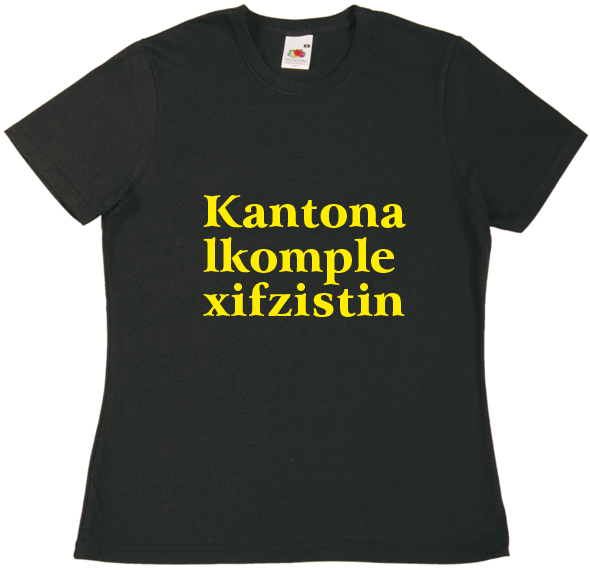
Umlaute in TTFs erstellen: simples Tool?
Komplexifizist!
Geil. Damit will ich ein T-Hemd.
Ist „Kantoniker“ eine Schweizer Spezialität? Irgendwie kommt mir der Begrif so gänzlich unbekannt vor…
:? Google kennt den auch nicht.
Bitte, wie können denn ausgerechnet Schriftgelehrte so unkreativ sein? :o
Während das Kirchenrecht den Kanoniker schon lange kennt, hat der Autor für den Fall der vorliegenden Polemik den "Kantoniker" eigens erfunden.
Dieser Begriff ist positiv diskriminierend. Er soll zeigen, dass Schweizer im Allgemeinen und die bezaubernde NinaS im Besonderen liebenswerte Sonderlinge sind, die ihr kleines Land in Kantone einteilen und dort glücklich Schokolade mit Offiziersmessern raspeln, ohne dabei auch nur im Geringsten auf die vielen äußerst präzisen Uhren zu schauen, die dort auf (Apfel-)Bäumen wachsen. Das alles macht einen echten Kantoniker aus.
Das Wort darf nach Vorstellung seines Urhebers ausschließlich mit Hilfe einer zutiefst schweizerische Schriftart dargestellt werden (z.B. GrüziTell boldi) , in der über jedem "ss" ein kleiner, durchbohrter Apfel abgebildet wird.
Aha! Und ich dachte schon, du meinst mit Kantoniker diese spanische Kartoffelsorte Iker, die wegen ihrer hohen Resistenz gegen die Erwinia-Schwarzbeinigkeit vielleicht auch im chinesischen Städtchen Kanton gerne angebaut wird. Was mich zweifeln ließ, ist der doch einigermaßen bekannte Hang vieler Chinesen zum Reis …
Geil. Auch die Farben sind klasse. Aber haste da auch, vielleicht, *ähem* eine andere Schrift? Ich steh nicht so auf so condensde Sachen. :neenee:
Bezgl. Umlaute und T-Hemde fällt mir übrigens gerade noch die tolle Geschichte von einem Kumpel meiner Cousine ein, der in einem Fußballfanclub namens «Höllenhunde» (!) Mitglied ist. Die haben sich Clubhemden bedrucken lassen, natürlich in schwarz und dann mit einer weißen Gebrochenen drauf, wie man sichs vorstellt. Und die Schrift gabs halt leider nur ohne Umlaute, tja. Nun steht da «Hoellenhunde» und meine Cousine spricht mit ihm seither konsequent im Stil von «Gell, das war scho-en heute, auch die Freisto-eße sind uns gut gelu-eckt». Ich könnte, pardon, ko-ennt mich wegschmeißen.
Wie endgeil ist das denn!?
So ein Shirt würde ich glatt meiner Frau kaufen, wenn sie Schweizerin wäre. Und ich ihr überhaupt was kaufen würde.
Wie endgeil ist das denn!?
So ein Shirt würde ich glatt meiner Frau kaufen, wenn sie Schweizerin wäre. Und ich ihr überhaupt was kaufen würde.
Aber haste da auch, vielleicht, *ähem* eine andere Schrift?
Wie jetzt? Eine andere Schrift? Du meinst ich sollte auf meinem Rechner eine Zweitschrift installieren? :shock: Man kanns auch übertreiben mit dem Kundendienst. Wir sind hier in Deutschland. Da hat man einen Ruf zu verteidigen als Dienstleistungswüste.
Nja, ich hab das letztens irgendwo gelesen, dass man das kann, so mehr als eine Schrift auf dem Rechner haben … hätte ja sein können, dass du … ach … :cry:
… Ich steh nicht so auf so condensde Sachen. :neenee:
Für dich: